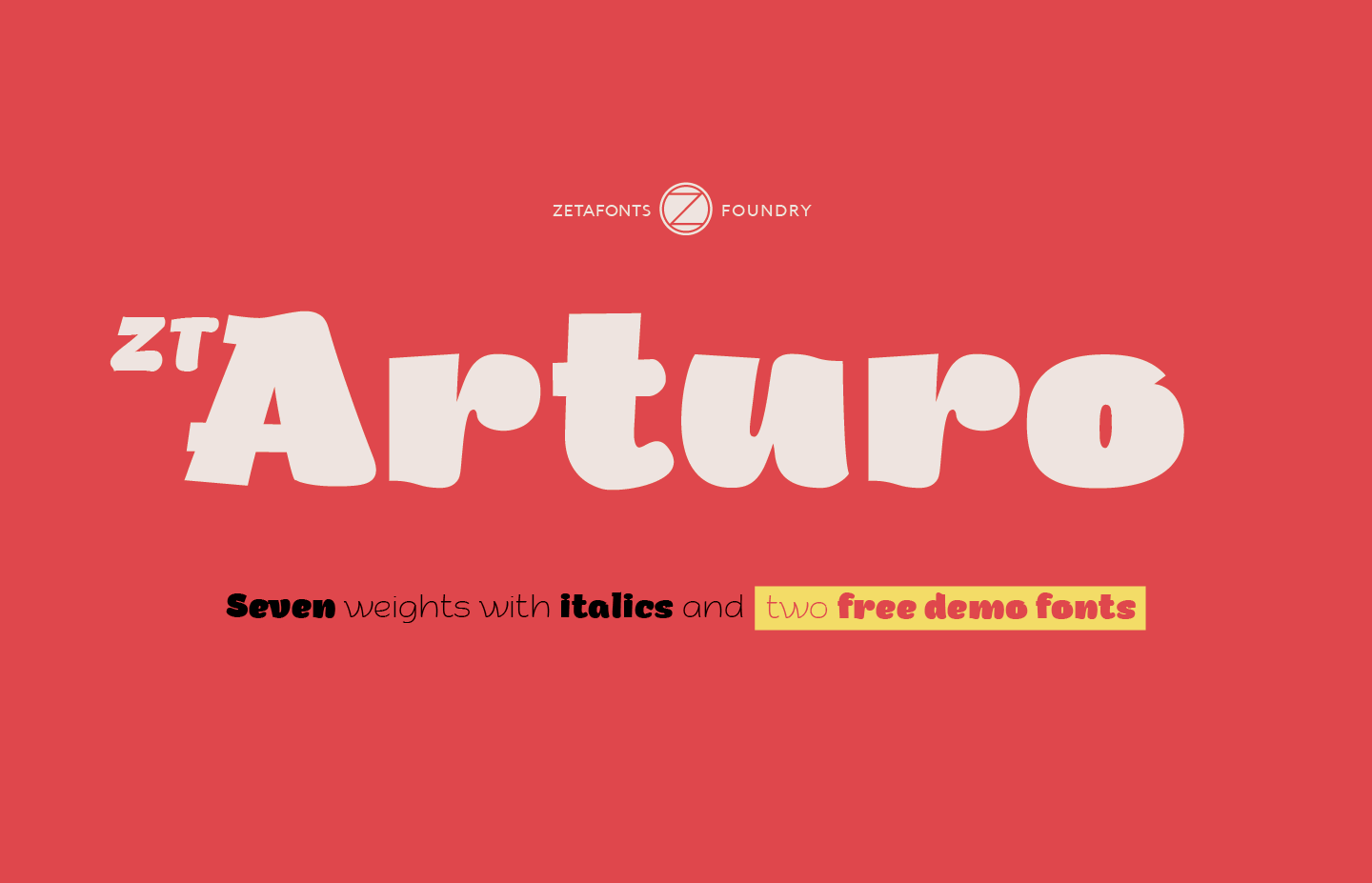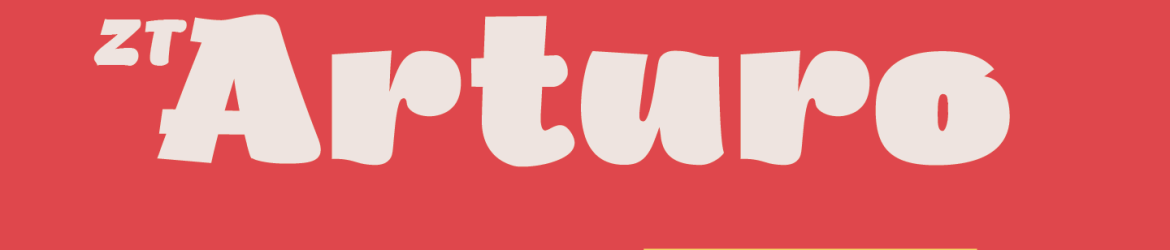
A introdução ao Arturo é uma descoberta fascinante para qualquer designer ou editor de texto que busca uma combinação única de estilo e funcionalidade. Introduzido por Francesco Canovaro através do Zetafonts, essa família de fontes incorpora um olhar descontraído e alegre às formas das letras em conjunto com a versatilidade necessária para uma família de textos multi-peso, além de recursos avançados como alternativas estilizadas, pequenos capítulos, ligaduras desconsideradas (para uso tanto no design de logotipos quanto no refinamento do texto), entre outros extras menos convencionais como numerais ordinais, numerais superiores e inferiores, figuras tabulares, linhas e antigas. Arturo é uma fonte extensiva que oferece sete pesos diferentes, todos acompanhados de itálico correspondente, tornando-a a escolha perfeita para qualquer projeto em busca de algo um pouco diferente no design do texto.